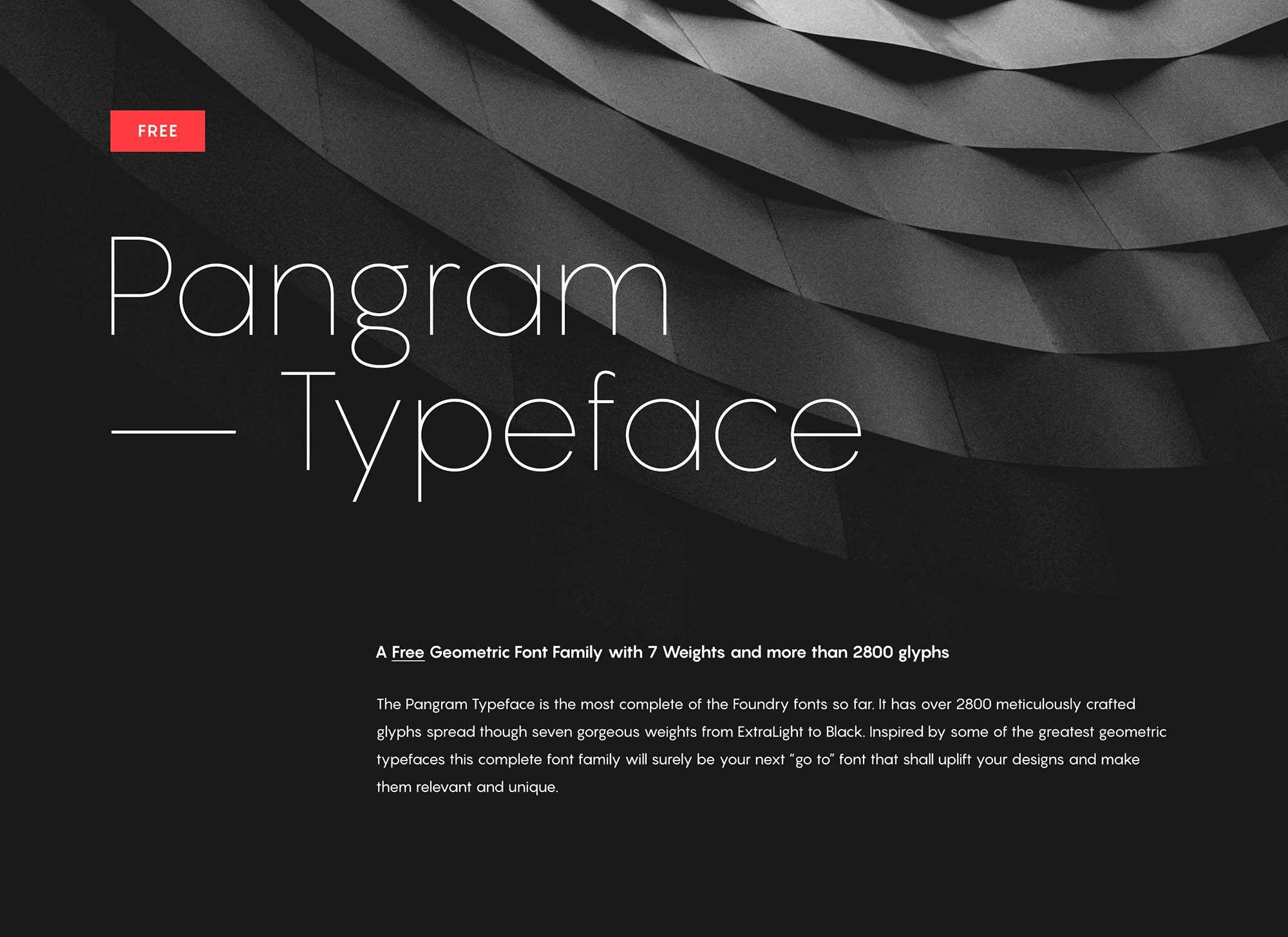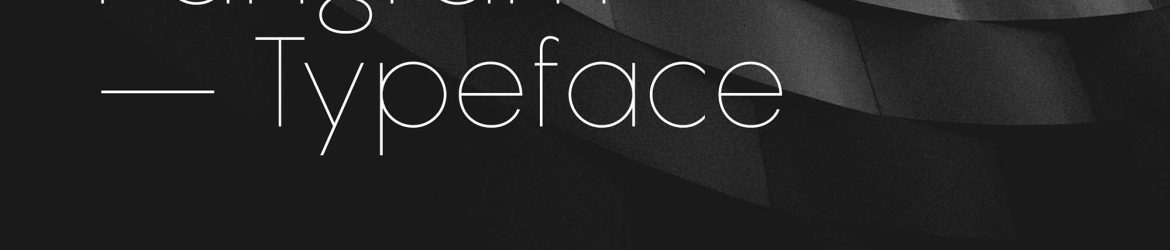
Este recurso gráfico chamou a atenção de designers por toda a categoria de mockups. Chamamos-lhe a atenção: Pangram Sans é uma nova sensação para os designers de recursos gráficos. Inspirado em tipos geométricos, este belo tipo de sans-serif extra leve certamente enfeitiçará seus trabalhos. Suas 2800 formas meticulosamente criadas estão distribuídas por sete belos pesos, do extra leve até o preto. É perfeito para criações de logotipos elegantes, materiais de embalagem, convites de casamento e capas de revistas ou livros modernos. Imaginamos que o seu design brilhará ainda mais em um lindo tom dourado ou numa cor metálica tendência, usada em embalagens de cosméticos ou sapatos. Seja qual for o seu próximo projeto, este é o tipo gráfico de design que você precisa. Não hesite em baixar e explorar esta bela font para melhorar seus designs.